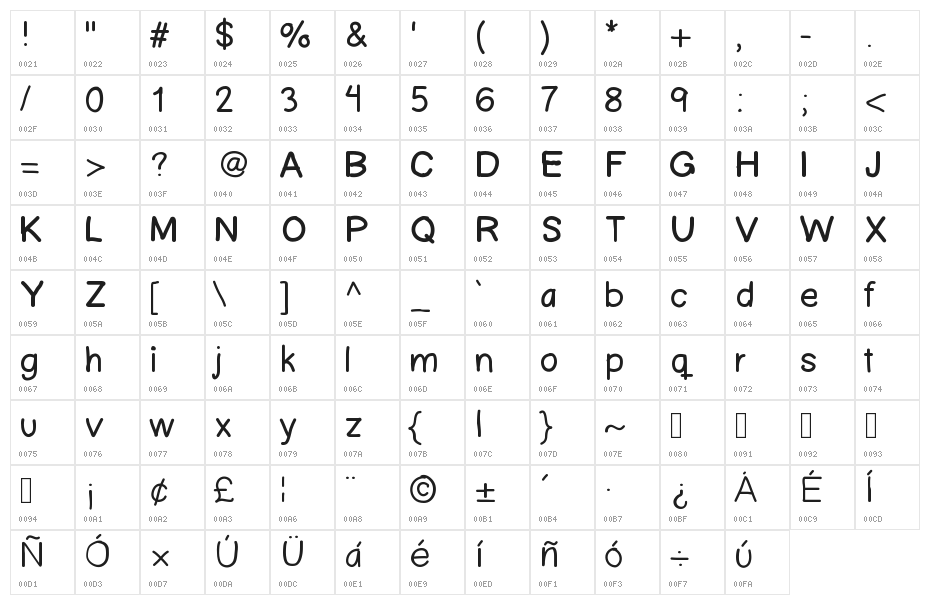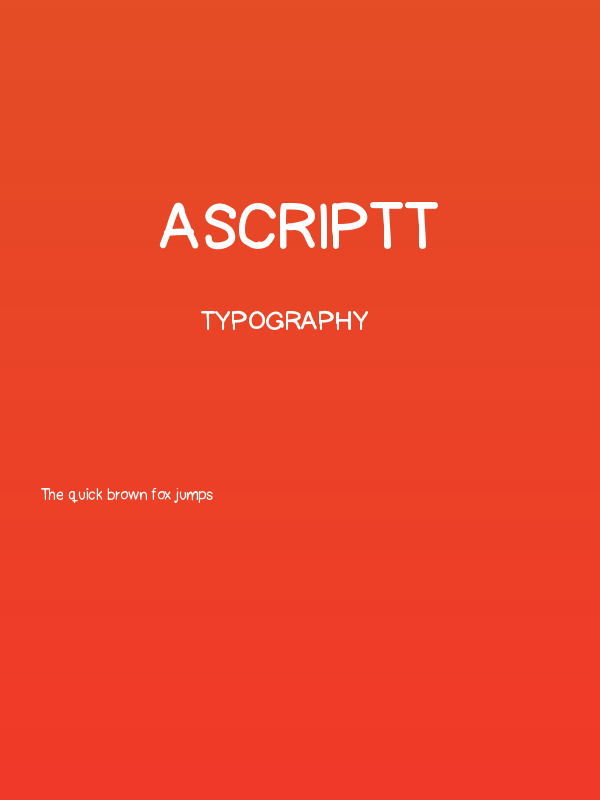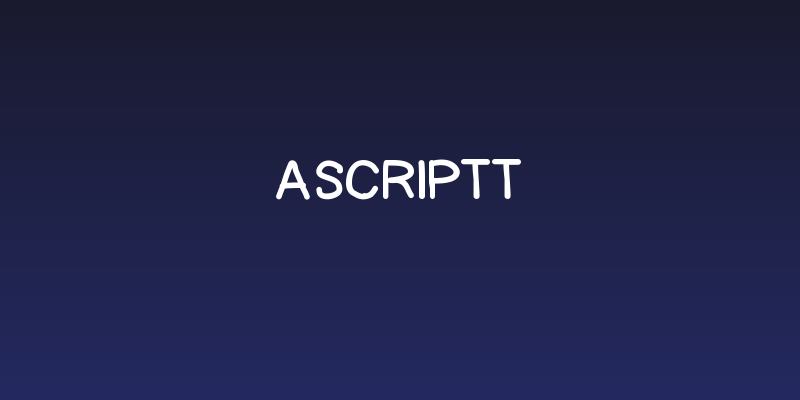
Ascriptt Font
| Gesamtstil | Casual |
| Anwendungsfall | Headlines, Logos, Invitations |
| Vorgeschlagene Projekte | Ideal for children's books, greeting cards, playful branding, and informal invitations. |